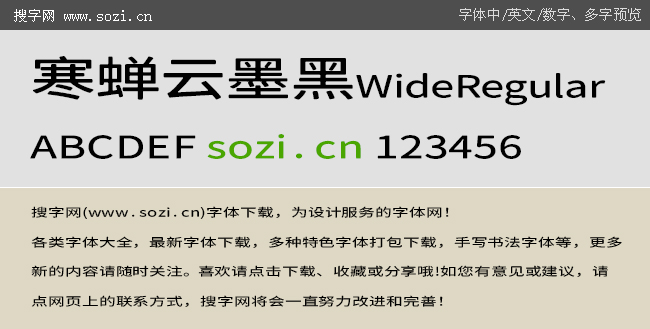
寒蟬云墨黑WideRegular
搜字網(wǎng)給大家提供一款寒蟬云墨黑WideRegular中文字體下載,寒蟬云墨黑是基于思源黑體進(jìn)行修改調(diào)整的一款黑體字體,字體添加了圓角,效果看上去更加溫潤(rùn)。排版細(xì)節(jié)也進(jìn)行了優(yōu)化,并重構(gòu)了字重比例。適用于標(biāo)題設(shè)計(jì)、海報(bào)設(shè)計(jì)、書(shū)籍排版以及網(wǎng)頁(yè)設(shè)計(jì)等應(yīng)用。